免費的注音字型,提供下載也可線上直接使用,附教學影片。新的IVS字型技術,一個檔案便可切換多音字的不同注音,比傳統多檔案的字型更方便。有右標注音、部首標明、或上標拼音,均附免費商用授權。
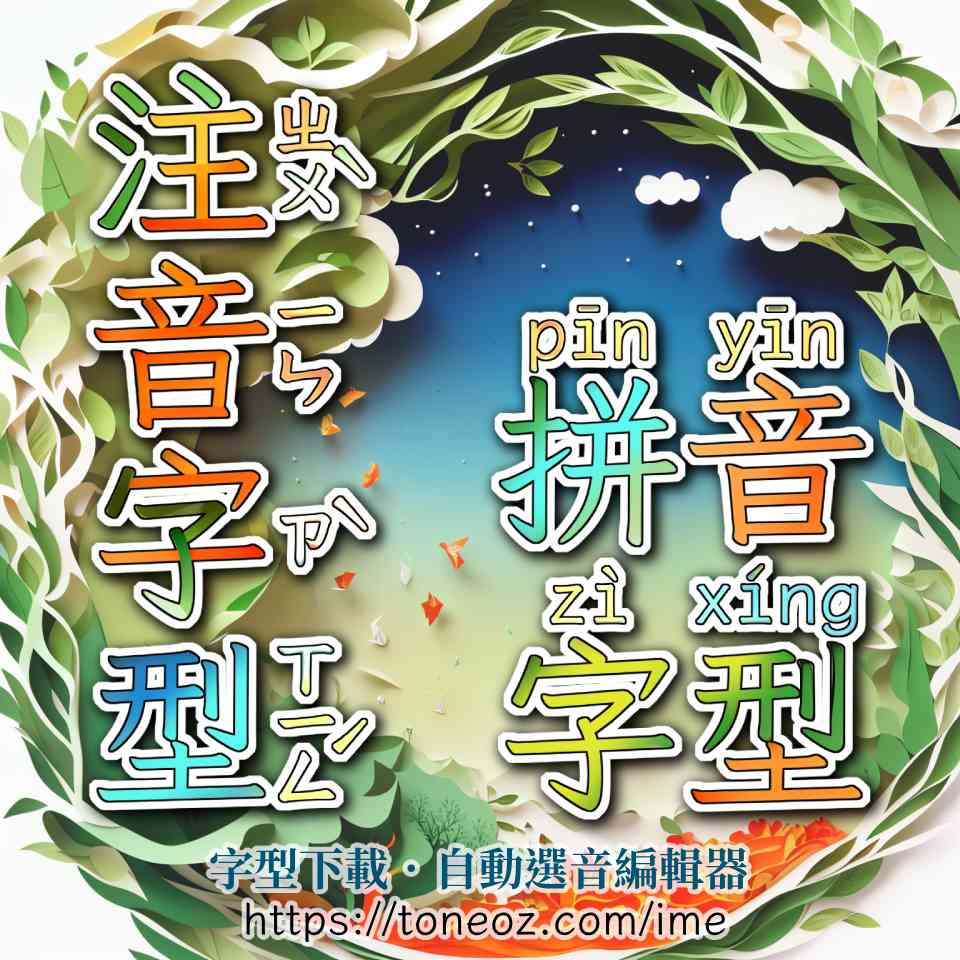
如何打出多音字
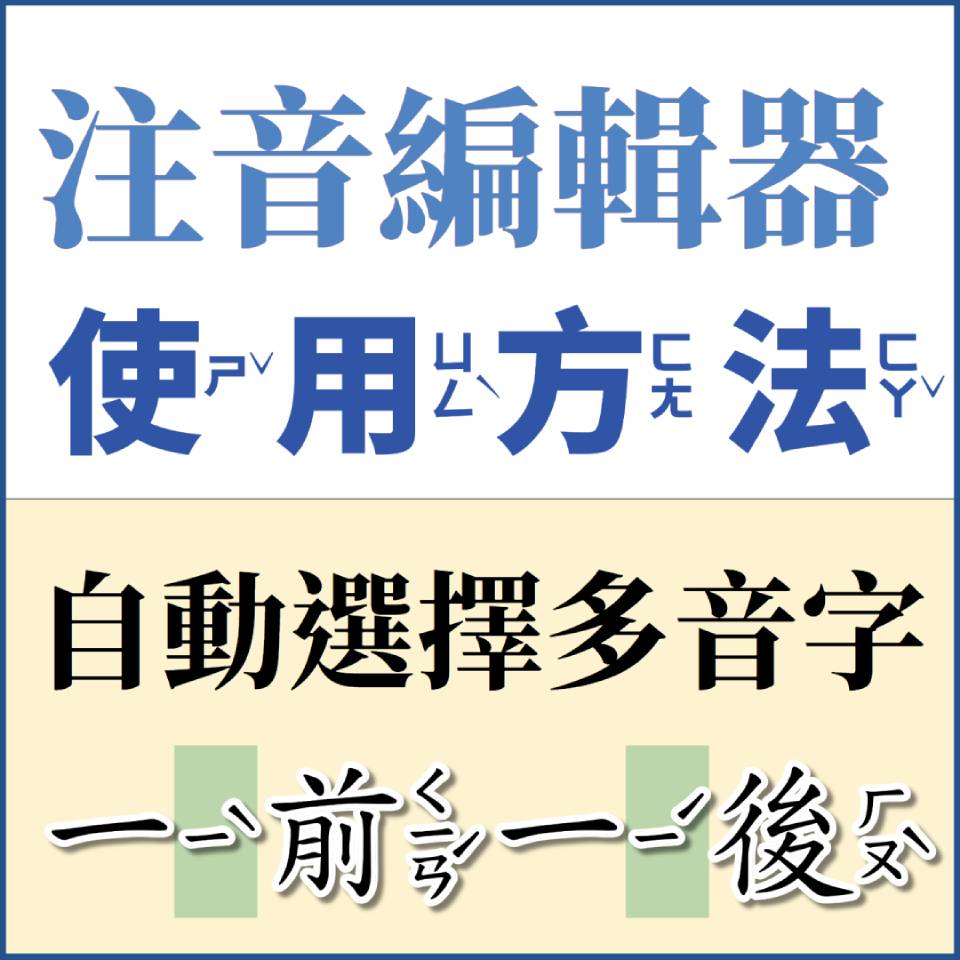
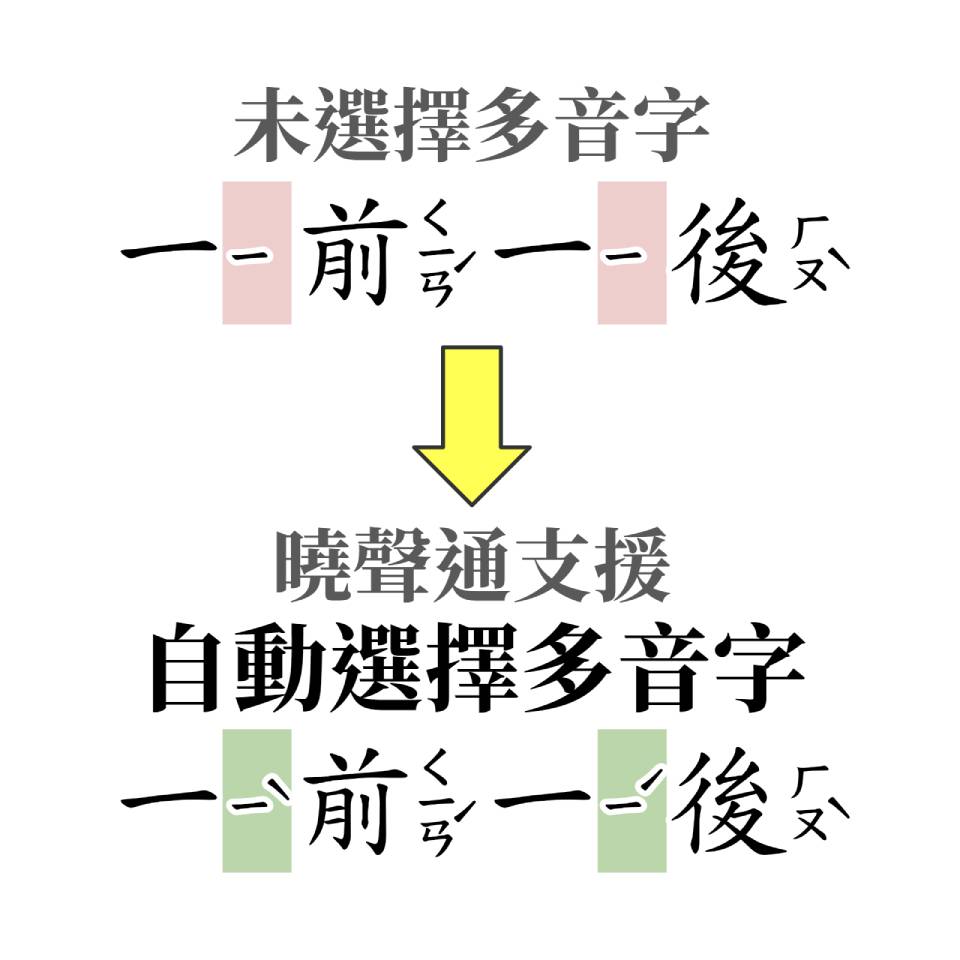
注音教育楷體
若您要編輯「標準楷體」國民中小學注音教材,那請下載「澳聲通庫楷(2.1萬字)」或「字嗨注音標楷(1.8萬字)」。兩套字型外型相同,都是基於「全字庫正楷體」(教育部免費授權的繁體標準字型,國中小教科書標準楷體)。
《澳聲通》 注音庫楷-繁
《字嗨》 注音標楷
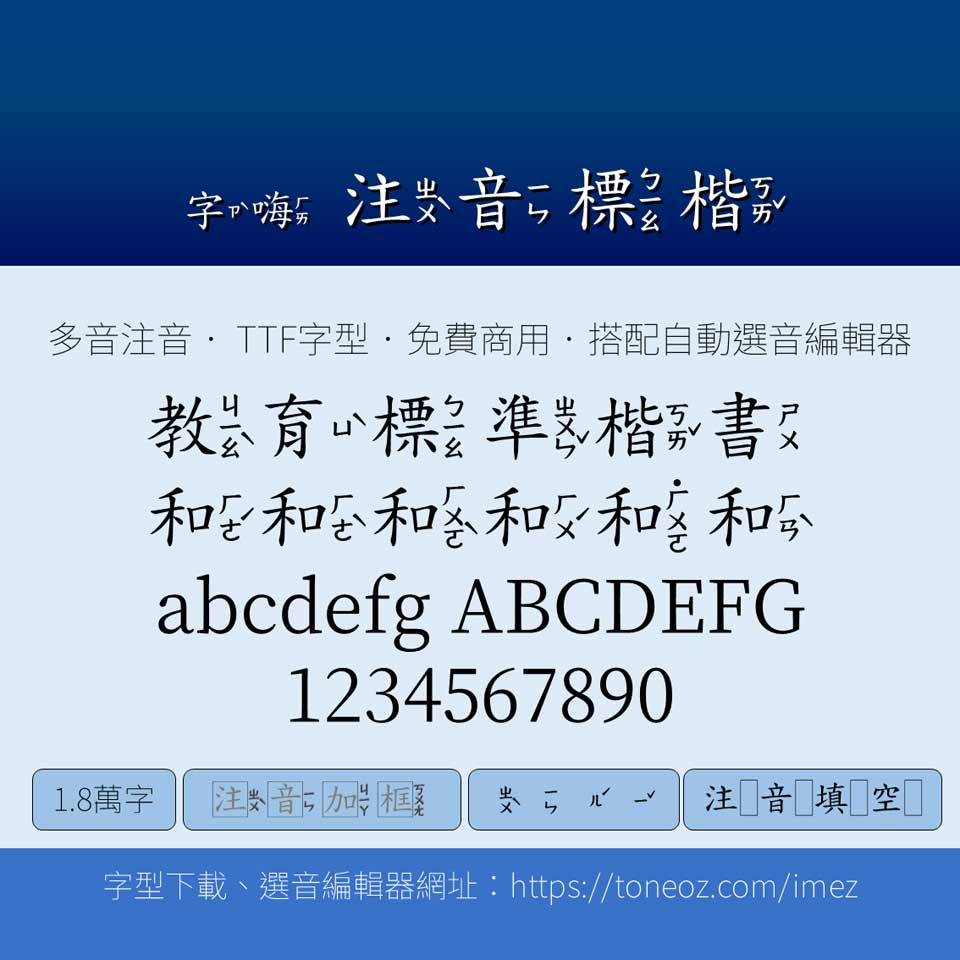
. 1.8萬字
. 教育部 全字庫正楷體
. 依教育部 一字多音審訂表
. 支援 注音加框
. 支援 注音而已
. 支援 注音填空
曉聲通秋茄 手寫字型
曉聲通「秋茄體」是開源免費的手寫字型,中性簽字筆風格,筆形符合國語教學《教師手冊》,由教育全文注音國語辭典 「曉聲通 」開發,涵蓋「教育部國語辭典」全條目,中小學考試標準「簡編本」常用字、及「重編本」「成語本」生僻字。以國字標準為前提,支援多元文化教案:閩南語、客家話、日本語、各式拼音、及港澳用字。
. 依照「教師手冊標準筆形」逐字校對
. 1.5萬字 涵蓋教育部三本國語辭典所有條目
. 補充閩南語客語用字
. 源自《隨峰體》
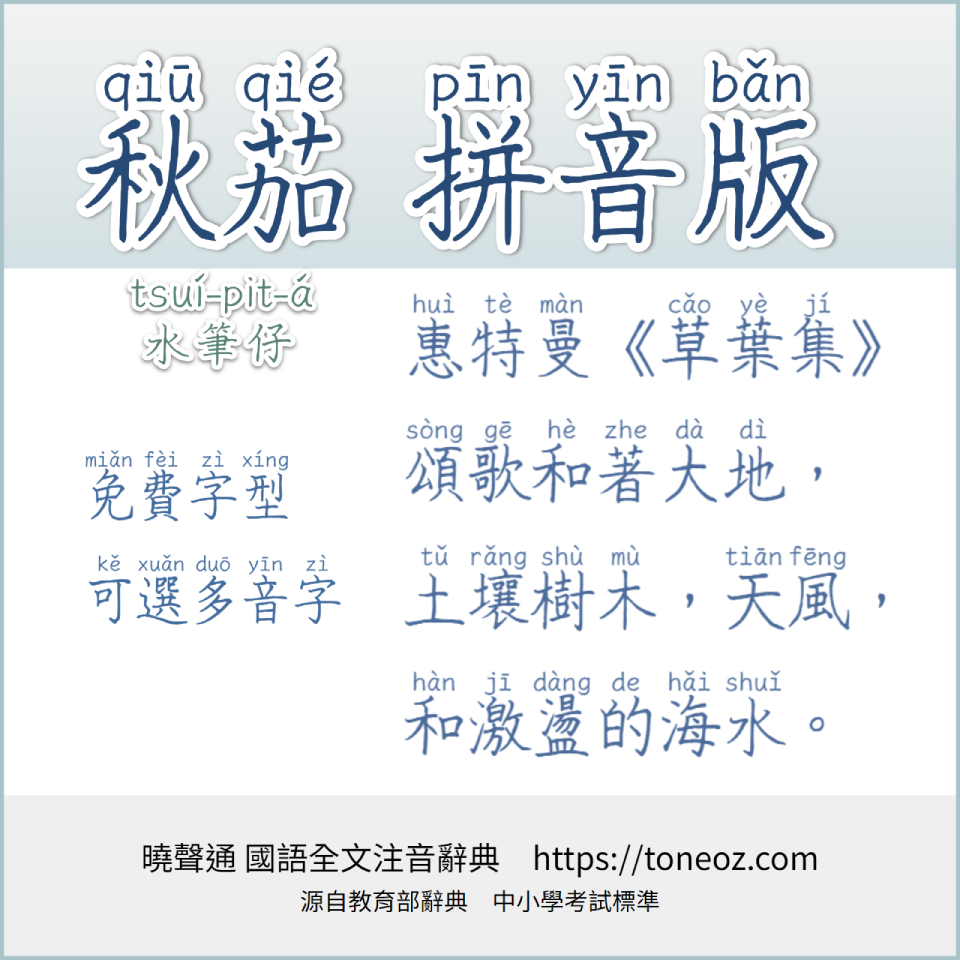
《曉聲通》秋茄雙拼注音版
仿宋楷體 (Fontworks Klee衍伸字型)
日本設計公司Fontworks旗下的字型 クレー(Klee),是麥金塔Mac內建的字型之一,兼具楷體的筆觸,及宋體的工整,外型優美適合閱讀。2020年底開放開源免費商用授權,許多愛好者以此為基底,延伸出多種適合教育場合的字型。
《字嗨》注音芫荽
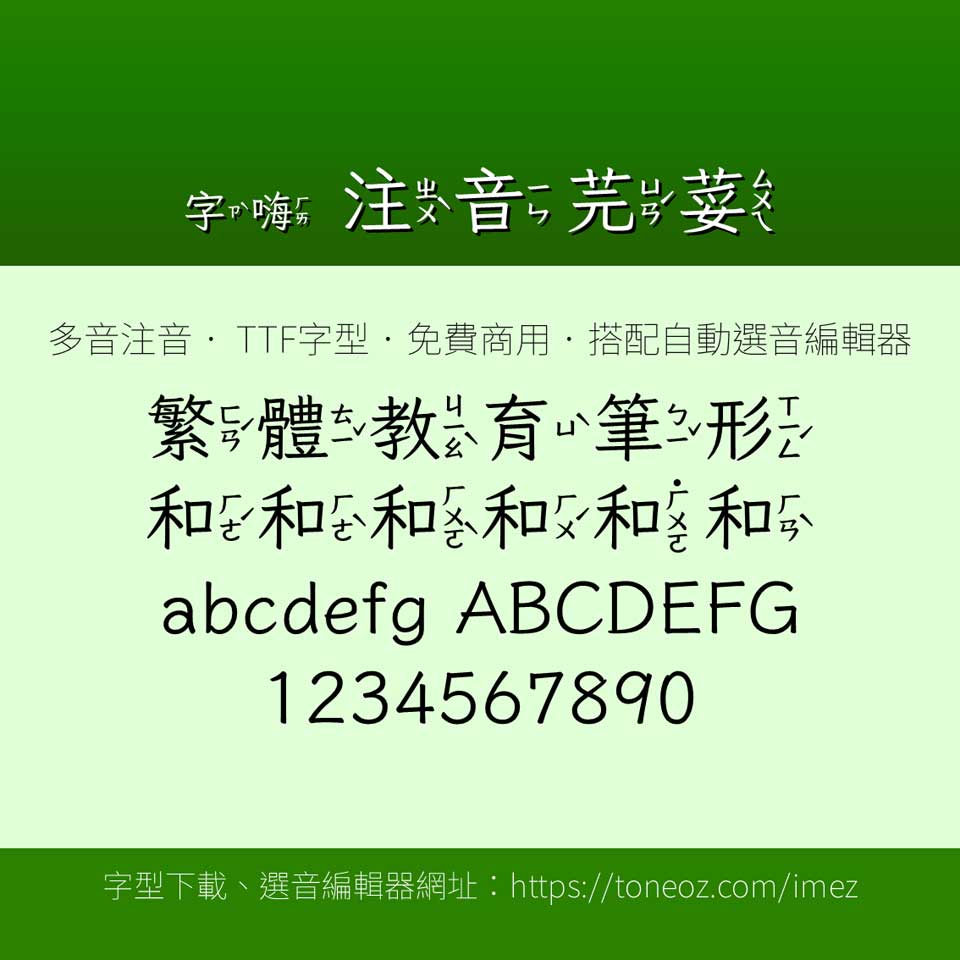
. 繁體教育筆形
. 源自 Fontworks Klee One
. 補充閩南語客語用字
《澳声通》拼音文楷
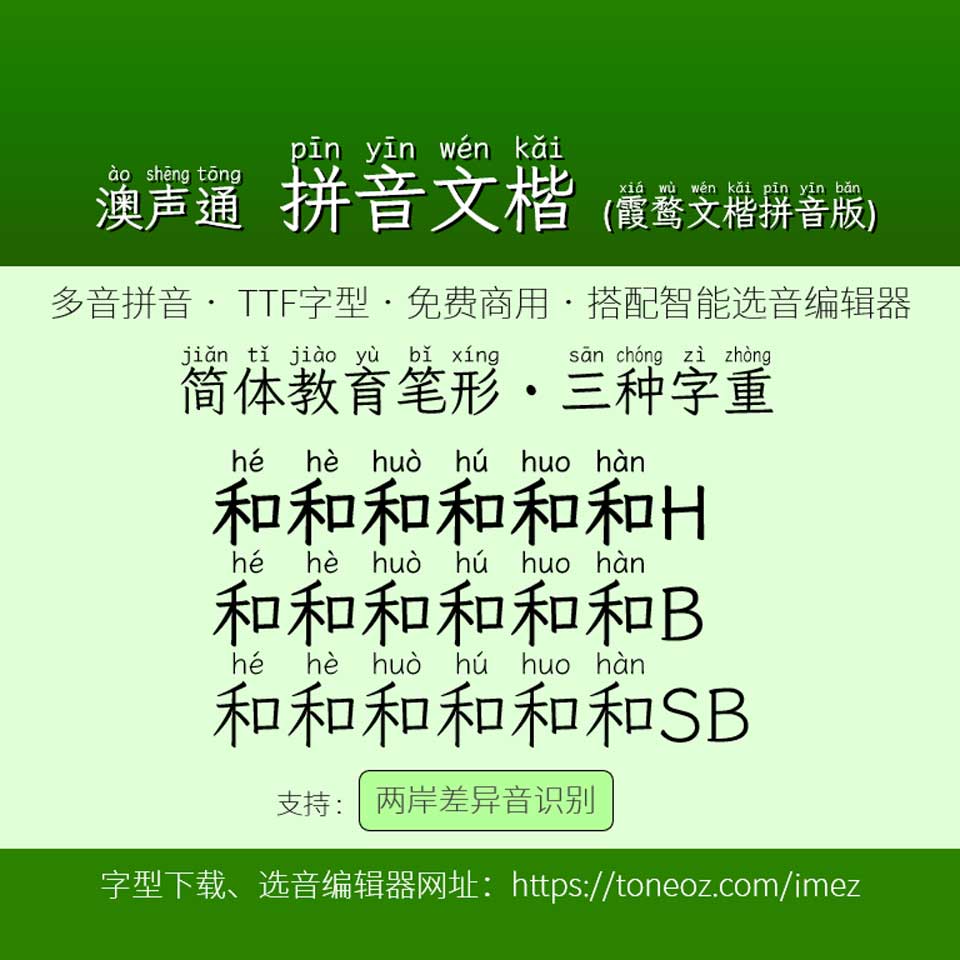
. 简体教育笔形
. 源自 Fontworks Klee One
. 霞鹜文楷GB 拼音版
漢語拼音教育楷體
搭配國際標準《ISO 7098中文羅馬字母拼寫法》的漢語拼音字型,適合熟悉羅馬字母的學習人士。依據繁簡教育標準筆順的字形差異,分別提供繁簡兩種字型。
《澳聲通》快雪拼音楷體-繁
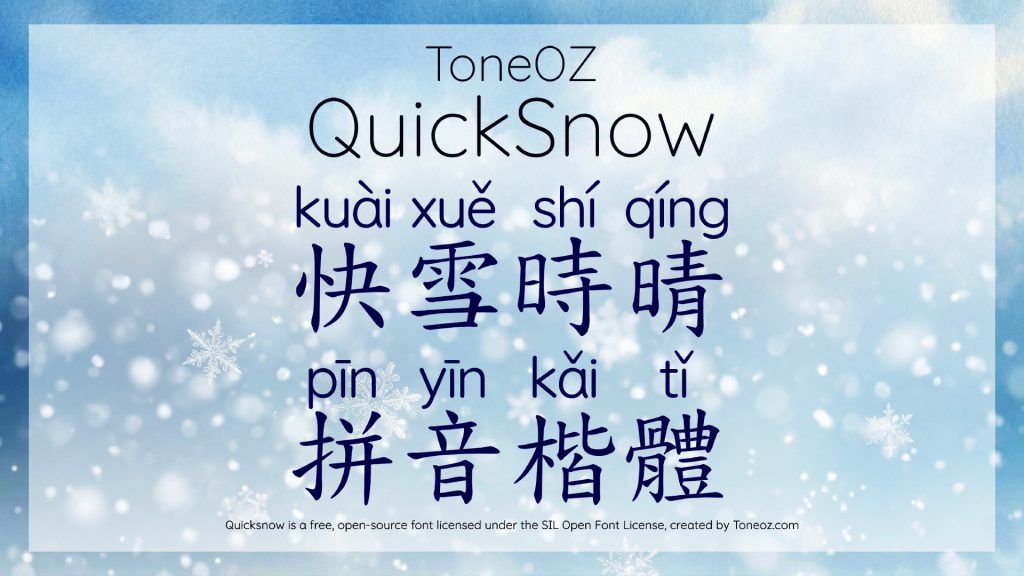
《澳聲通》拼音庫楷-繁
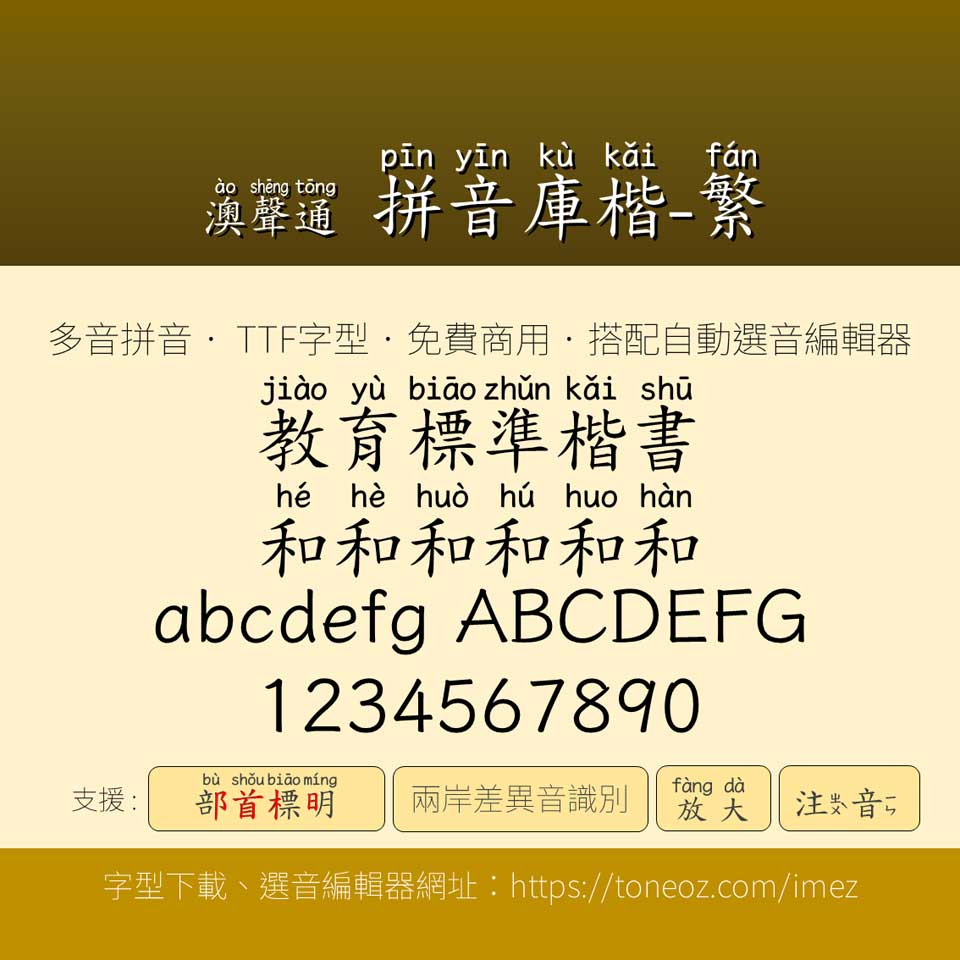
. 2.1萬字
. 教育部 全字庫正楷體
. 依教育部 一字多音審訂表
. (附加)教育部重編本參考音
. (附加)兩岸差異音辨識
. 支援 部首變色
. 支援 拼音放大
. 支援 注音
注音美感字型
除了標準楷體以外,以下還有八種由字嗨But Ko製作的圓體、黑體、或明體等不同風格的字型,同樣是免費商用授權。下載前請先確認一下您的教材種類:
- 嚴謹製作國民中小學「國語」科目教材
建議用「字嗨黑體」或「字嗨宋體」,這兩個字體的筆型貼近國字標準字體。 - 其他科目一般教材
可任選字體。
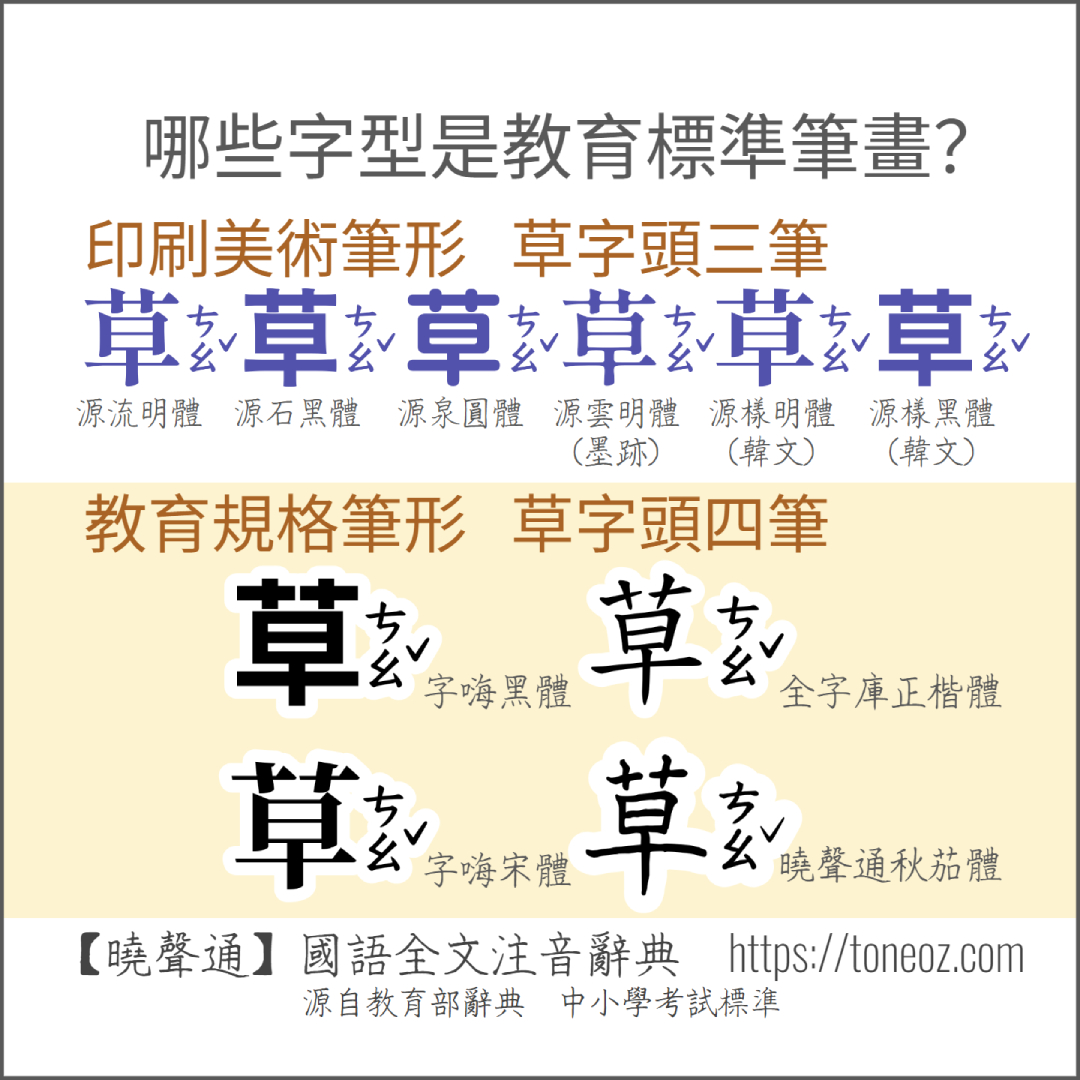
《字嗨》注音黑體
. 源自《思源黑體》
. 六種字重
《源石》注音黑體
. 源自《思源黑體》
. 起筆收筆加上粗細變化
. 五種字重
《源樣》注音黑體
. 源自《思源黑體》
. 韓文版思源黑體漢字
. 七種字重
《字嗨》注音宋體
. 源自《思源宋體》
. 七種字重
《源流》注音明體